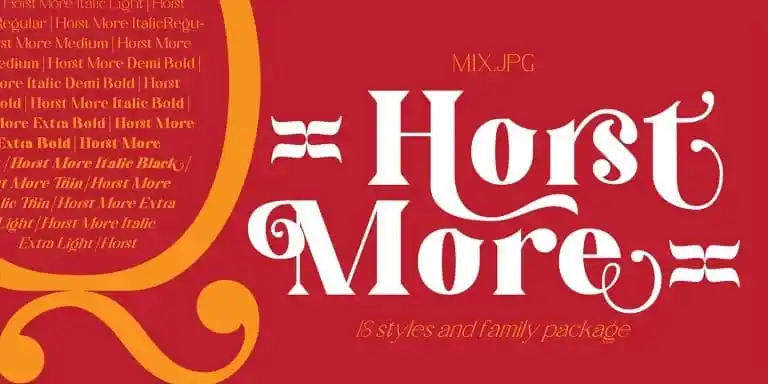
Horst More Serif Font – Download Grátis
A Fonte Horst More Serif é uma opção elegante e divertida para qualquer projeto que precise de caracteres serifizados, seja para identidade visual ou conteúdo principal. Com 18 tipos de letras distintas, a herança serifada desta fonte faz dela um ícone à parte no mundo dos recursos gráficos digitais. Sua curvatura suave e ligeiramente ondulada é o que torna essa fonte única em sua categoria. Ela se adapta perfeitamente para uma ampla gama de aplicações tipográficas, desde criação de marca até para o texto principal, com sua variedade de pesos que garantem legibilidade natural. A versão do tipo familiar é ainda mais interessante quando você começa a aplicar as ligaturas e alternativas aditivas. Estas características adicionais não apenas fazem uma diferença significativa no estilo final da fonte, mas também tornam-a ainda mais versátil em termos de criação de composições tipográficas originais e agradáveis aos olhos do usuário. Sua proposta é perfeita para quem quer criar mensagens amigáveis com um visual que desperta interesse imediato.